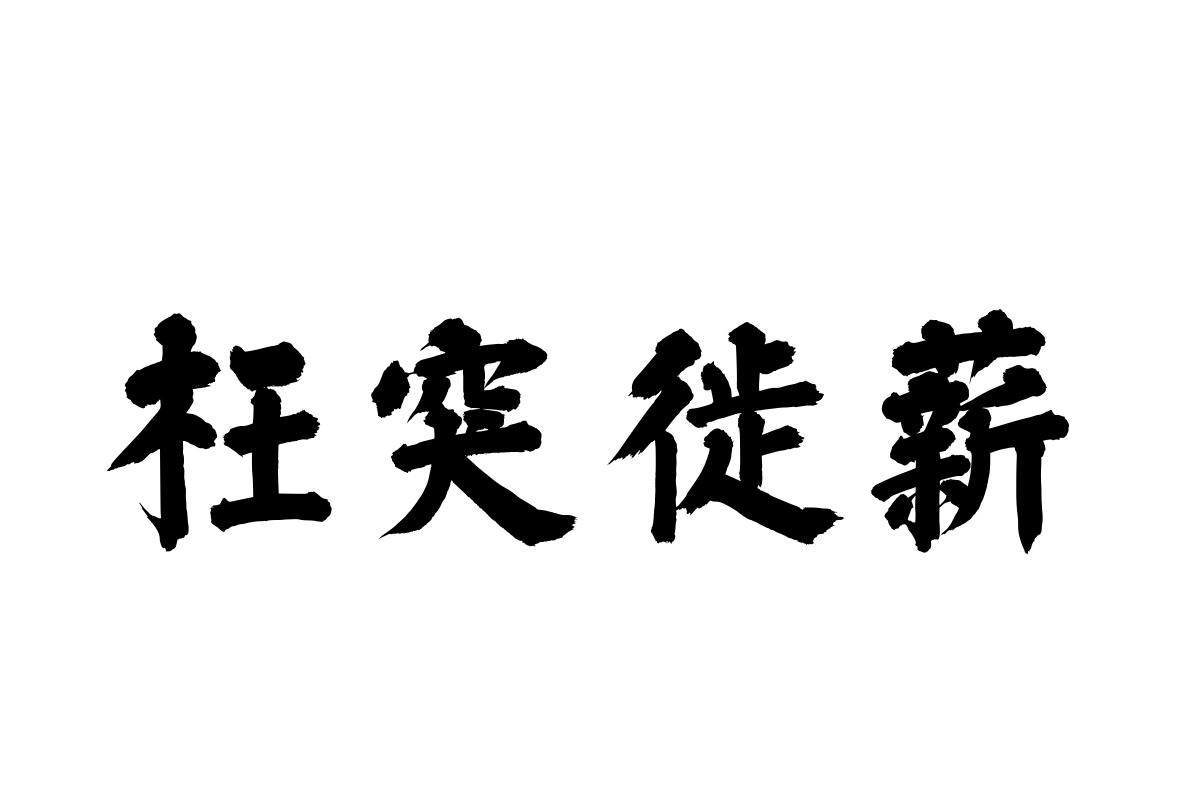
汉仪老字号字体是一款具有深厚文化底蕴的中文字体,由汉仪字库公司设计制作。这款字体以其独特的书法风格和优美的线条,深受广大用户的喜爱和青睐。
汉仪老字号字体的特点主要有以下几点:
1. 历史悠久:汉仪老字号字体源自中国古老的书法艺术,经过多年的传承和发展,已经形成了独特的风格和韵味。
2. 书法韵味:汉仪老字号字体的笔画流畅自然,结构严谨,具有很强的书法韵味。无论是楷书、行书还是草书,都能展现出优美的线条和韵律感。
3. 易于识别:汉仪老字号字体的字形规整,笔画清晰,易于识别和阅读。同时,字体的大小、间距和行距都经过精心设计,使得整体排版更加美观大方。
4. 适用范围广泛:汉仪老字号字体适用于各种印刷品、广告、包装、网页等场景,具有较强的实用性和通用性。
5. 文化内涵丰富:汉仪老字号字体不仅仅是一种视觉元素,更蕴含着丰富的文化内涵。它代表着中国古老的书法艺术,传承了中华民族的文化精髓。
总之,汉仪老字号字体是一款具有深厚文化底蕴的中文字体,无论是从书法韵味、易识别性、适用范围还是文化内涵等方面来看,都是非常优秀的选择。